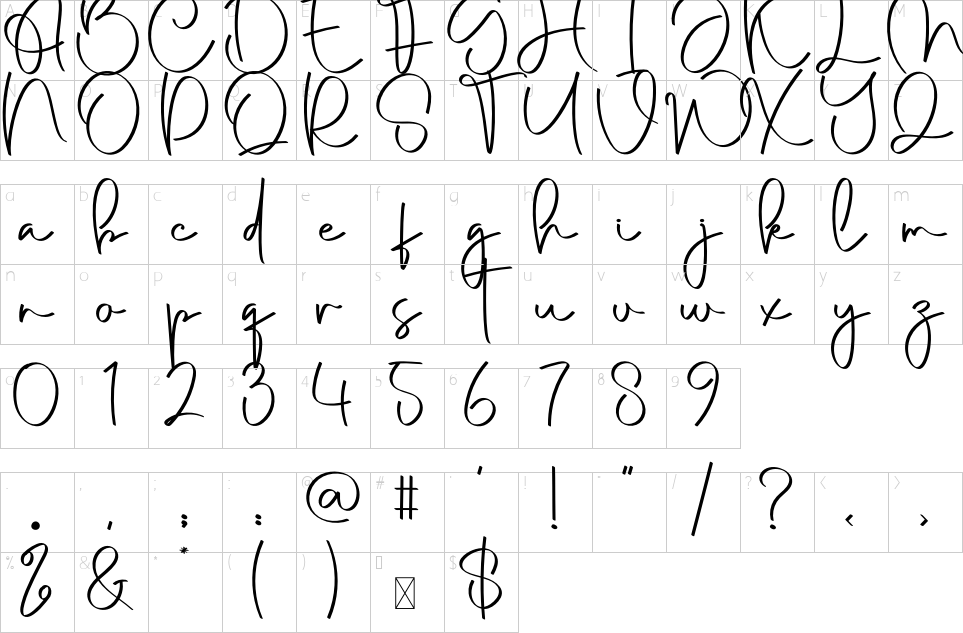
Autography Font
A fonte Autography é uma escolha perfeita para designers e aficionados por textos, proporcionando um estilo elegante e moderno. Desenvolvida pelo designer desconhecido scratchones, Autography é uma fonte grata disponível tanto para Windows quanto para Mac. Sua estética suave e sofisticada torna-a perfeita para aplicativos de design gráfico, editoriais e websites, onde deseja adicionar um toque único e moderno. Com 594 downloads desde seu lançamento, é evidente que designers de todo o mundo estão apreciando o charme e a versatilidade da Autography. Se você está procurando por um estilo de fonte para destacar em seus projetos, vale a pena explorar esta opção gratuita.
Mapa de caracteres da fonte Autography Font